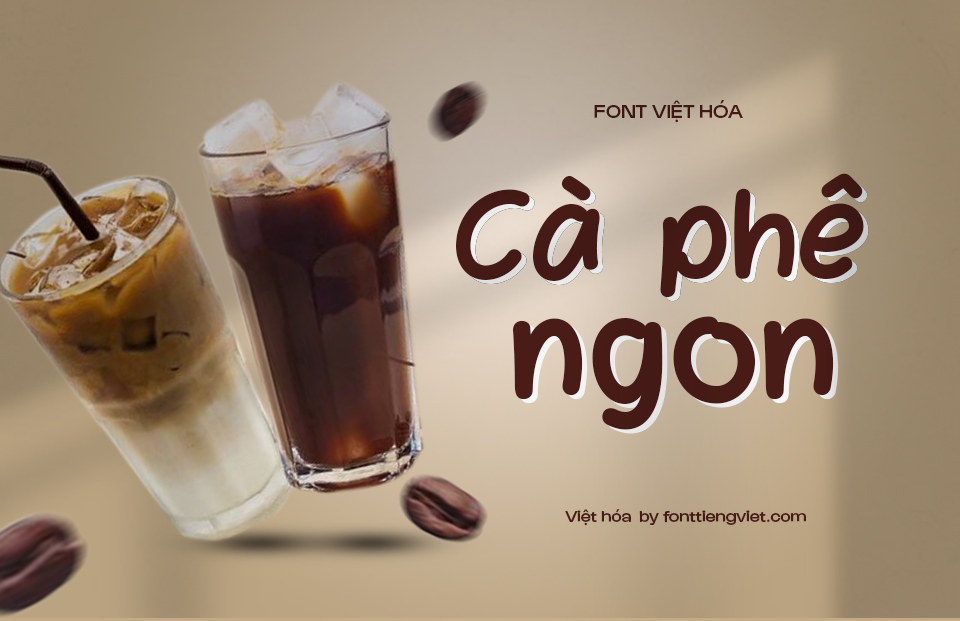
Font Việt hóa 1FTV VIP Mulled Wine Season
Giới thiệu về Font Việt hóa 1FTV VIP Mulled Wine Season
Trong thế giới thiết kế đồ họa hiện đại, việc lựa chọn một bộ Font Miễn Phí chất lượng luôn là ưu tiên hàng đầu của các designer. Đặc biệt, bộ Font Việt hóa 1FTV VIP Mulled Wine Season đang trở thành tâm điểm chú ý nhờ phong cách độc đáo và sự tinh tế trong từng đường nét. Đây là một phông chữ mang đậm hơi thở của những mùa lễ hội ấm áp, lấy cảm hứng từ hương vị cay nồng của rượu vang nóng bên bếp lửa. Với phiên bản Việt hóa hoàn chỉnh, người dùng có thể dễ dàng sử dụng các ký tự tiếng Việt có dấu mà không lo bị lỗi hiển thị, giúp quy trình sáng tạo trở nên mượt mà và chuyên nghiệp hơn bao giờ hết.
Đặc điểm nổi bật của Font Việt hóa 1FTV VIP Mulled Wine Season
Bộ phông chữ này sở hữu cấu trúc chữ cái thanh thoát nhưng không kém phần chắc chắn, tạo cảm giác thân thiện và gần gũi cho người xem. Các nét chữ được bo tròn mềm mại, mô phỏng lại những nét vẽ tay thủ công khéo léo, mang đến một vẻ đẹp nghệ thuật rất riêng. Điểm cộng lớn nhất chính là khả năng hiển thị sắc nét trên cả màn hình kỹ thuật số lẫn bản in truyền thống. Dù bạn đang thiết kế một tấm thiệp chúc mừng, bìa sách hay giao diện website, phông chữ này đều đáp ứng tốt các tiêu chuẩn thẩm mỹ khắt khe nhất hiện nay.
Ứng dụng thực tế của Font Việt hóa 1FTV VIP Mulled Wine Season
Sự linh hoạt là yếu tố then chốt khiến Font Việt hóa 1FTV VIP Mulled Wine Season được yêu thích rộng rãi trong cộng đồng sáng tạo tại Việt Nam. Phông chữ này không chỉ giới hạn trong các dự án cá nhân mà còn len lỏi vào nhiều lĩnh vực chuyên nghiệp khác nhau. Nhờ sự kết hợp hài hòa giữa cổ điển và hiện đại, nó giúp truyền tải thông điệp một cách cảm xúc và ấn tượng hơn tới khách hàng mục tiêu.
Sử dụng trong thiết kế truyền thông và thương hiệu
Đối với các chiến dịch marketing mùa đông hoặc các sản phẩm thủ công, bộ font này là sự lựa chọn hoàn hảo để làm tiêu đề bài viết hoặc logo thương hiệu. Sự ấm áp tỏa ra từ các đường nét giúp tạo dựng niềm tin và sự thoải mái cho người tiêu dùng. Ngoài ra, trong môi trường giáo dục, giáo viên có thể sử dụng phông chữ này để trang trí bảng tin hoặc làm giáo án điện tử, giúp các bài học trở nên sinh động và thu hút học sinh hơn. Tính ứng dụng cao giúp nó trở thành một công cụ đắc lực cho bất kỳ ai muốn nâng tầm thẩm mỹ thiết kế của mình.
Tối ưu hóa nội dung với Font Việt hóa 1FTV VIP Mulled Wine Season
Khi sử dụng phông chữ này, bạn nên chú ý đến việc kết hợp khoảng cách giữa các chữ cái (kerning) để đạt được hiệu quả thị giác tốt nhất. Việc phối hợp nó với các font chữ không chân (sans-serif) đơn giản sẽ tạo ra sự tương phản thú vị, giúp làm nổi bật những thông tin quan trọng nhất. Đây là một bí quyết nhỏ nhưng cực kỳ hữu hiệu trong việc xây dựng hệ thống phân cấp thông tin rõ ràng cho các sản phẩm thiết kế đồ họa chuyên nghiệp.